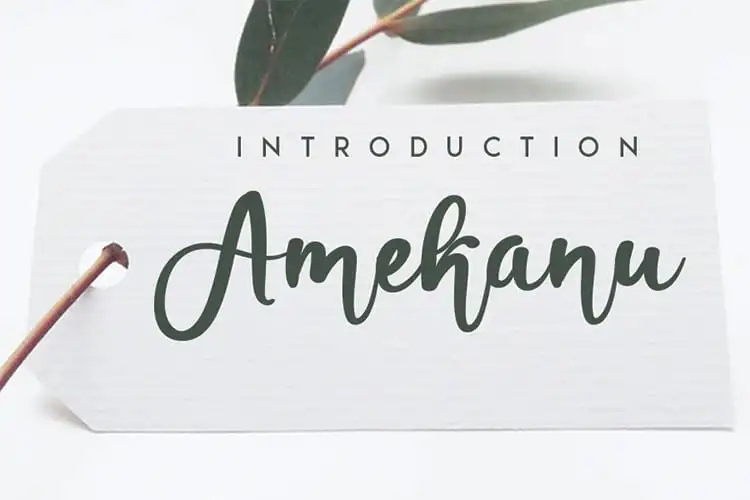
Descubra a autêntica elegância do Amekanu Script Font nas mãos do designer eikastudio. Especialmente criado para estilos de escrita manuscrita, esta fonte é uma escolha perfeita para projetos que valorizam um toque pessoal e único. Seja no formato de logotipo social, embalagem de produto ou até mesmo em um projeto de arte fotográfica, este estilo inovador convida a experiências memoráveis e personalidades sólidas. Ideal tanto para aplicações tradicionais como publicações digitais, o Amekanu Script Font é uma opção perfeita para projetos que exigem um toque autêntico de escrita. Seja você criando uma campanha de marketing emocionante, um projeto de logomarca única ou até mesmo uma série de publicações de moda elegante — o Amekanu Script Font está pronto para ilustrar sua visão e dar vida ao seu trabalho.